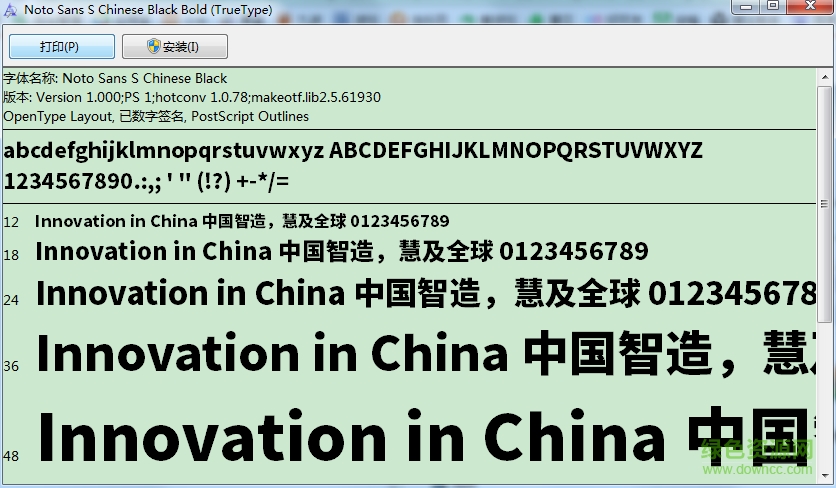
notosanshans black是一款經(jīng)典的英文字體,這款字體線條粗壯,結構嚴謹,能給人傳達出強勁的意味,適用的范圍也非常廣泛,歡迎大家來綠色資源網(wǎng)免費下載使用。
notosanshans black是一款非常好看的英文字體,筆畫粗壯,十分醒目,適合用于廣告設計、排版印刷等領域,喜愛的朋友趕快到綠色資源網(wǎng)下載體驗吧!